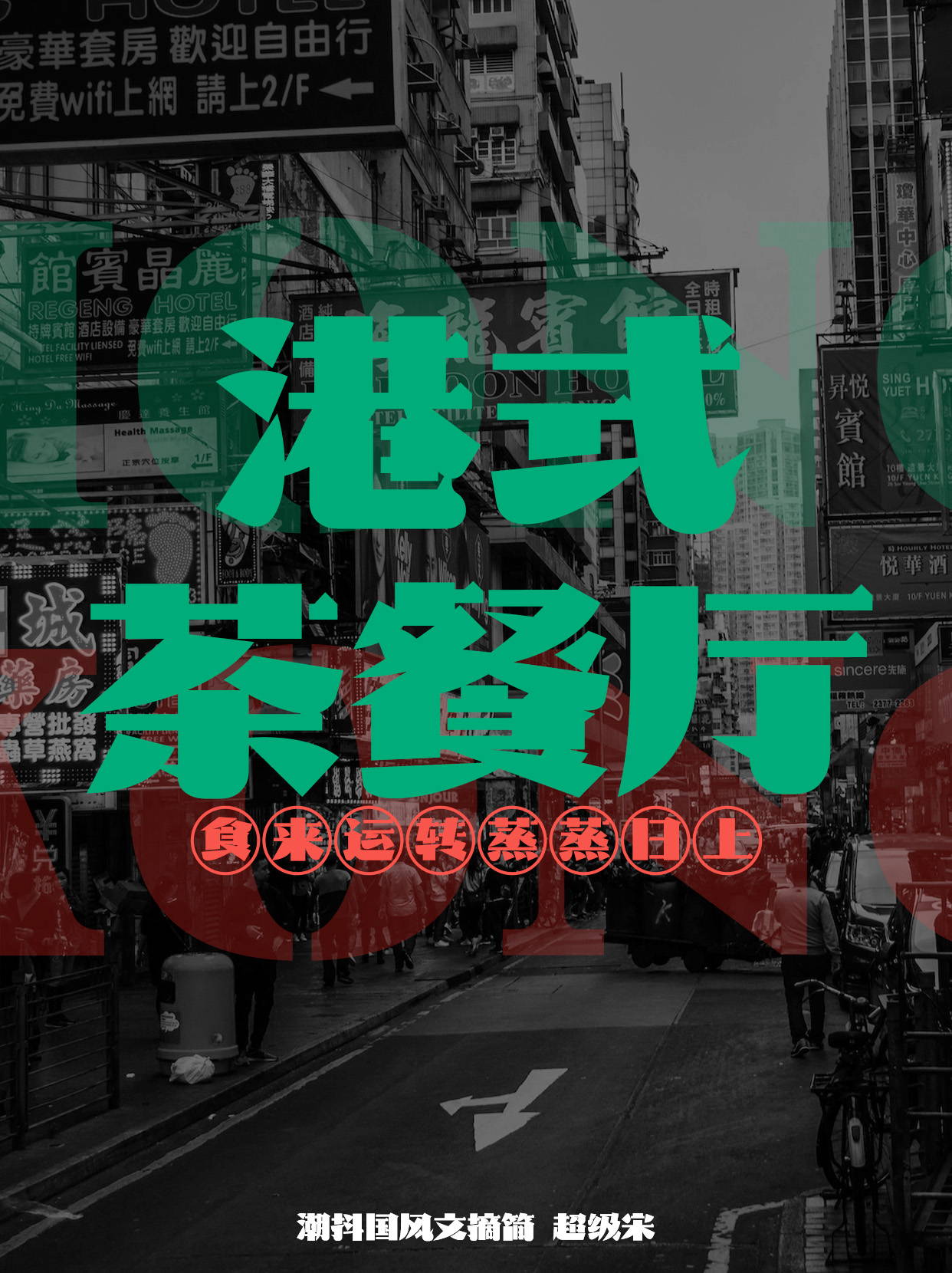
该字体是一款具有复古式的字形与现代宋体完美结合于一体的美术宋体。加入笔画断笔切割特点,字型较扁又带有些许圆润感,布白合理。横笔画末端和折笔处加入斜角装饰特点,点笔画和捺笔画加入圆弧的特点,极具复古式的宋体特点,笔画间进行断笔处理,更加简洁易读,撇、捺、点、提部分笔画根据空间弧度等运用断笔的表现方式,给予字体呼吸感和统一的视觉风格。